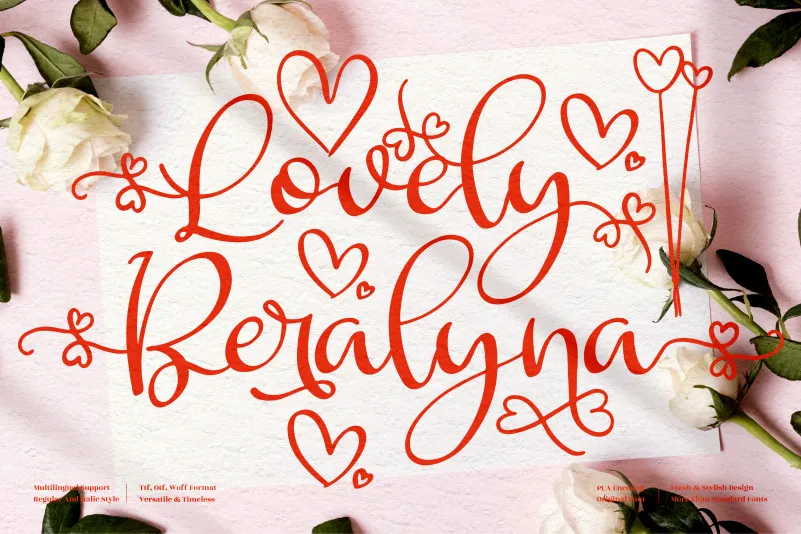
A fonte ‘Lovely Beralyna’ é uma delicada tipografia romântica ideal para projetos variados. Seu charme se destaca não apenas no design, mas também na sua versatilidade. Perfeita para criações de logomarcas e identidades corporativas, as fontes ‘Lovely Beralyna’ são uma escolha perfeita para designs de móveis de escritório, embalagens de produtos, sacolas de shopping, camisetas personalizadas ou até mesmo etiquetas. O seu encanto se faz presente em cartões de convite e cartas de cumprimento, capas de livros, selos de fotografia, adesivos para eventos especiais. Este script é a escolha perfeita para quem busca uma decoração com um toque delicado e romântico. Não há limitação aos seus usos; este design se adequa a todos os tipos de projetos que precisam daquela pitada de elegância e bom gosto.